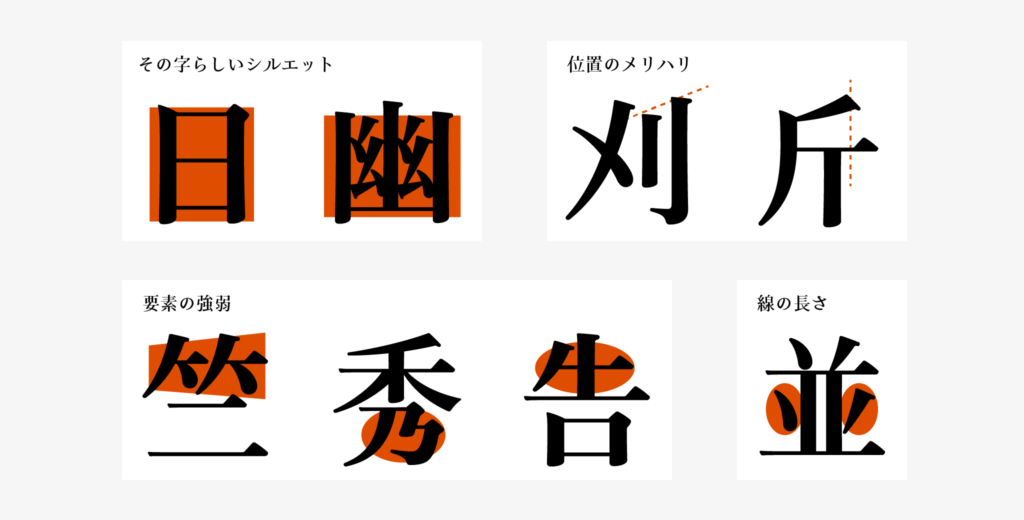
純明朝開発ストーリー2「骨格の特徴 その2」
前回の記事では、純明朝の漢字は縦方向に引き締まっていると書きました。単にフトコロを同じ方向に引き締めればよいのではなく、各々作り方は異なります。純明朝で作り方が特徴的なものや、難しかった例をいくつか挙げてみます。
「日」や「幽」などは他の字とのバランスや大きさ、その字らしいシルエットを意識せずに、縦方向に引き締まった他の字と同じように作ると単に細長くなってしまいます。
「刈」は、りっとうの起筆位置の高さの差をやや強調したり、「斤」では一画目の始まる位置を左に寄せて下にくる横画との位置関係にメリハリをつけています。
「竺」の竹冠では、左右の大きさや太さの差をつけて動きが出るようにしています。右にややせり出すようなイメージです。「秀」の下にくる「乃」の要素はかなり小さめに、「告」は一番上にくる横画の位置を下げるなどして頭の部分を引き締めています。これらは要素の強弱をつけている作り方です。
「並」の点と左ハライなどの要素はやや短くして、すっと速く引く線の速度を意識しています。
上記の特徴や大きさの比率によって、横組みでは漢字と仮名の固有の表情、仮名の脈略や筆の動きが見えやすく、縦組みでは仮名と漢字がともに引き締まっているため縦方向に目が流れるようにラインが揃いフラットで、字面いっぱいの漢字を持った明朝体とは違う印象があります。それを特徴付けている引き締まった漢字の骨格をどのように制作していったか、次回の記事で紹介します。